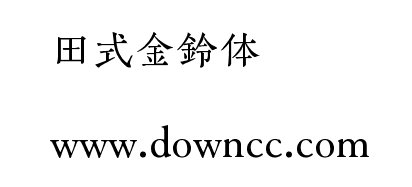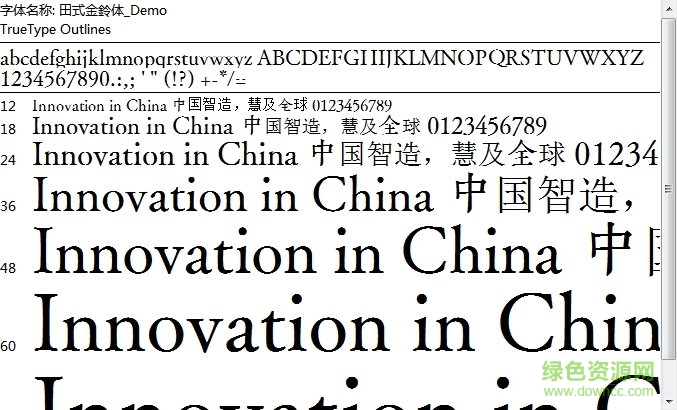
金鈴體完整版是一款日本書法家創(chuàng)作的中文字體,只有測(cè)試版的田氏金鈴體demo版,字庫(kù)不夠完整,但常規(guī)的書寫還是能滿足的,如果你需要就來(lái)綠色資源網(wǎng)試試吧!
田式金鈴體運(yùn)用古籍復(fù)刻技術(shù),給您古色古香、原汁原味的文字享受!